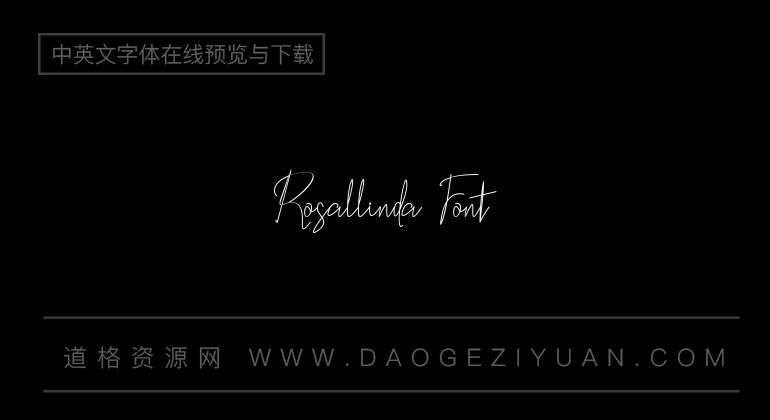
Rosallinda Font
Rosallinda Font是一种手写风格的字体,由Indonesia-based designer Ardyana Types设计。这种字体具有流畅的线条和轻松的笔画,适用于多种设计场景,例如卡片、手写风格的标志、海报、宣传册等。它包括大写和小写字母、数字、标点符号和一些特殊字符。该字体的特点是具有良好的可读性和明亮的外观,适合用于需要注重轻松和友好氛围的设计。
Rosallinda Font是一款非常不错的手写艺术字体,具有很好的视觉感,适合于文化类的宣传设计、商业类品牌的广告和产品包装设计以及个性化文字排版等较多场景。